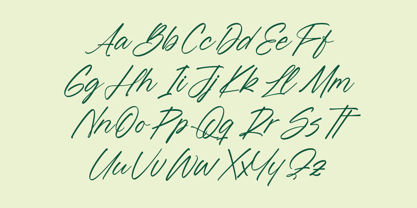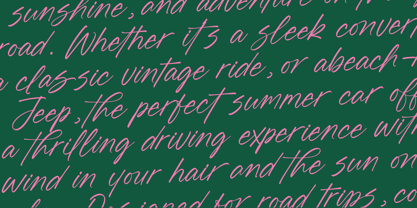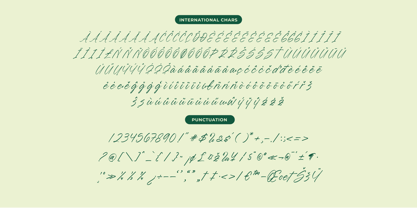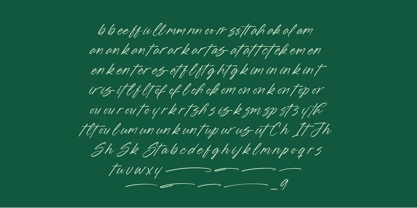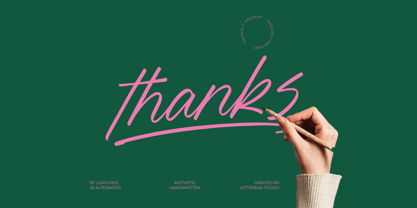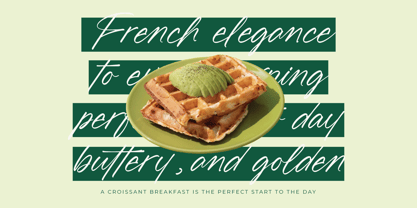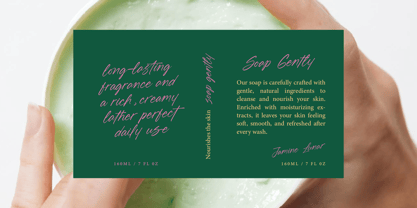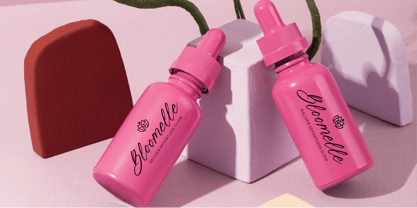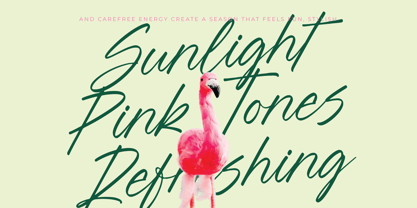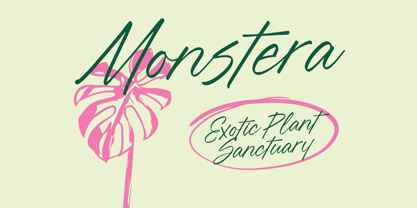
Blynkas Scripte
von Letterena Studios
Die Schriftfamilie Blynkas Scripte wurde von Heru Utama Putra entworfen und von Letterena Studios veröffentlicht. Blynkas Scripte enthält 2 Stile und Familienpaketoptionen. Mehr über diese Familie
Blynkas Scripte - Aesthetic Handwritten Font , from Letterena, is a Luxury Script font, suitable for any projects such as: logos, branding projects, homeware designs, product packaging, mugs, quotes, posters, shopping bags, t-shirts, book covers, name card, invitation cards, greeting cards, label, photography, watermark, special events, and all your other luxury and beautiful projects that need a Luxury Script taste.
Designer: Heru Utama Putra
Aktuelle Foundry: Letterena Studios